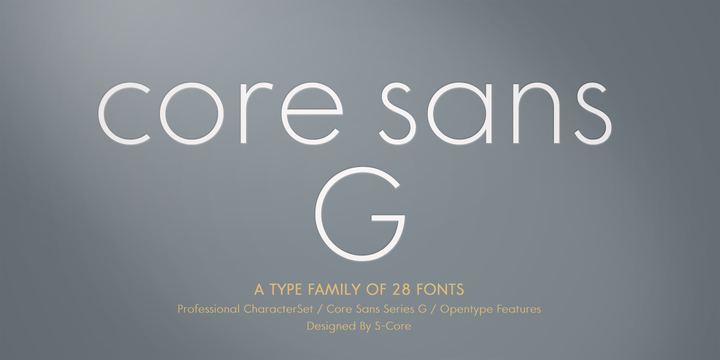
A Core SansG é uma família de fontes do tipo sans-serif que faz parte da série Core Sans. Inspirada no equilíbrio elegante entre linhas retas e formas geométricas, essa família oferece um conjunto amplo de opções com diferentes tipographies e estilos, permitindo a criação de designs únicos. O designer Hamilton criou uma linha de fontes versáteis que podem ser usadas para projetos variados – desde design gráfico até layouts web. A Core SansG é projetada para oferecer um equilíbrio entre elegância e simplicidade, proporcionando texturas e gráficos dinâmicos sem deixar de lado a legibilidade essencial dos tipos de fontes do tipo sans-serif. Essa família está disponível em uma variedade de estilos – incluindo cores suaves que podem ser usadas para contraste ou complemento. A Core SansG é perfeita para aqueles buscando um equilíbrio harmônico entre modernidade e elegância, tornando-a uma escolha ótima para qualquer projeto visual, seja ele digital ou impressão.